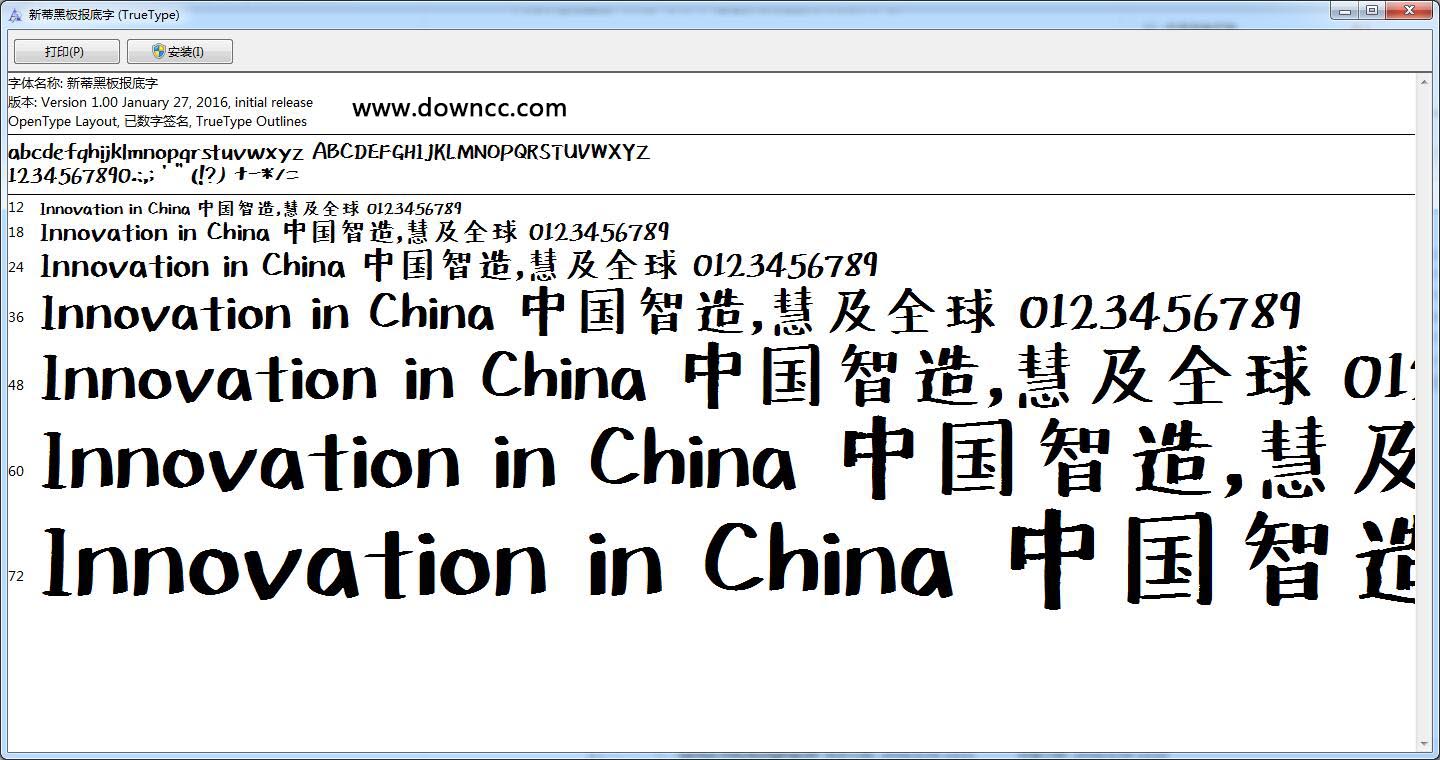
新蒂黑板報(bào)底字是一款適用用于設(shè)計(jì)行業(yè)的字體應(yīng)用!字體整體上比較大方霸氣,文字效果突出!喜歡這款字體的用戶歡迎來本站下載!
新蒂黑板報(bào)底字是一款專為黑板報(bào)而設(shè)計(jì)的中文簡(jiǎn)體字體,這款字體可謂字形大氣,可以應(yīng)用于藝術(shù)設(shè)計(jì)、平面廣告等行業(yè)!需要的用戶歡迎在綠色資源網(wǎng)下載使用!